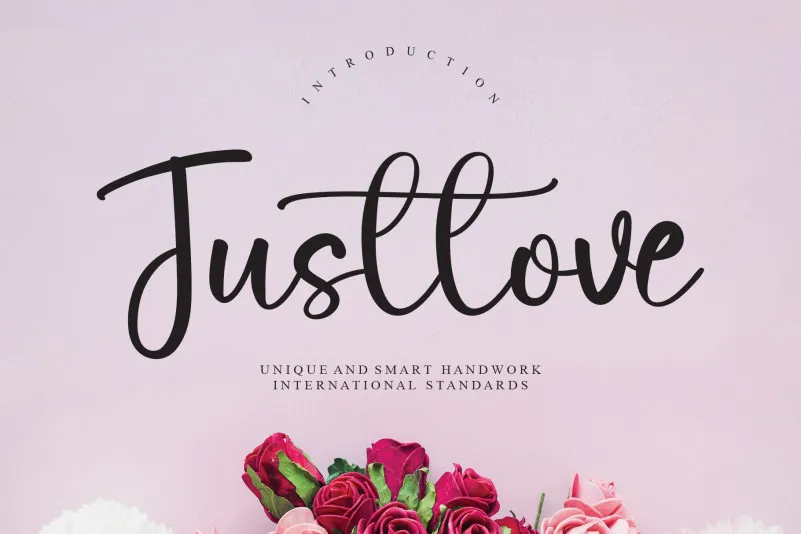
Justlove Script Font – Download Grátis
Esta fonte ‘Justlove Script Font’ é perfeita para quem busca adicionar uma pitada única à sua criação digital. Desenvolvida por creativeletter, esta fonte escrita a mão oferece um toque de criatividade e personalização inigualável para designers apaixonados. Com linhas levemente desenhadas e formas sutis que remetem ao estilo do papel manual, essa fonte é uma escolha perfeita para quem procura um efeito atraente e original no seu design. Seja você criando um design gráfico complexo ou simplesmente adesivo, essa fonte entrega um toque especial que tornará sua obra ainda mais única. Ideal tanto para designers quanto para amantes da arte digitais, ela oferece flexibilidade na criação de qualquer projeto que você possa imaginar.